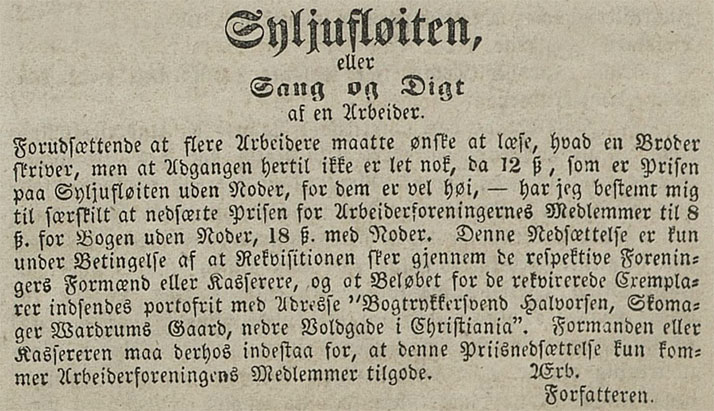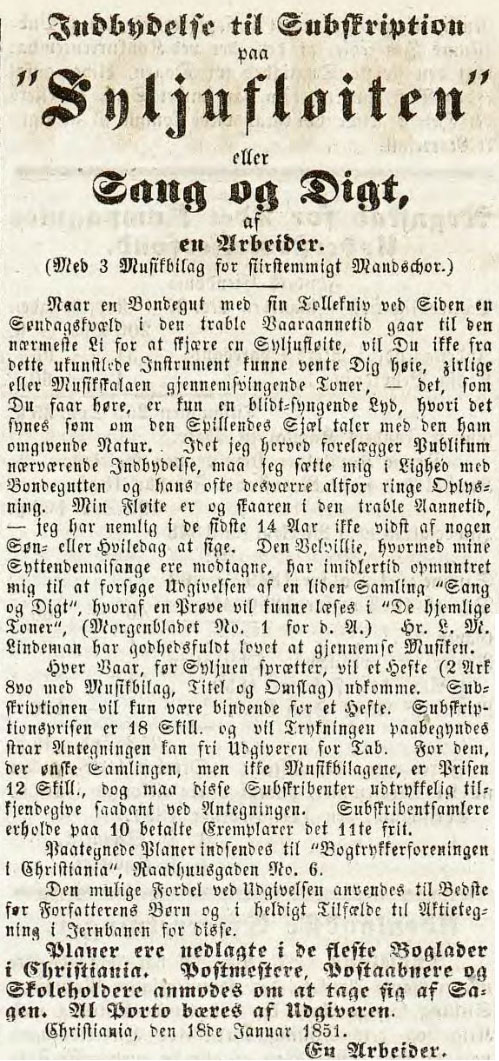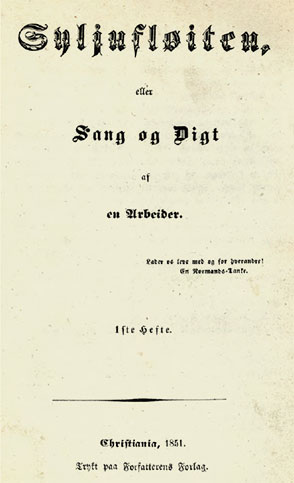
Typograf Christopher Daniel Grøndahls utgivelse fra 1851
Syljufløiten: tidlig norsk arbeiderdikting
Diktsamlingen Syljufløiten (seljefløyten i moderne språkdrakt) ble gitt ut i 1851. Forfatteren er «en Arbeider», som vi vet var typografen Christopher Daniel Grøndahl. Han var en ledende kraft i en tidlig organisering blant boktrykkersvennene i Christiania – Bogtrykkerforeningen af 1849.
I tillegg til at Syljufløiten er et uttrykk for en poetisk, skrivefør arbeiders tanker, inneholder den også politiske synspunkter som kaster lys over tidens meningsforskjeller i arbeiderklassen. Dette var nemlig den perioden da Marcus Thranes radikale arbeiderforeninger spilte en stor rolle i Norges politiske liv.
«Indbydelse til Subscription paa ‘Syljufløiten’ eller Sang og Digt, af en Arbeider» lyder overskriften i en annonse i Morgenbladet 7. mars 1851. Annonsen er datert 18. januar, så hvorfor det tok så lang tid å få den inn i bladet kan vi bare spekulere over.
I annonsen skriver forfatteren at det planlegges et hefte «Hver Vaar, før Syljuen sprætter» og trykkingen vil begynne når antall abonnenter er stort nok til at utgiveren ikke går med tap. Prisen for ett hefte var 18 skilling med noter og 12 skilling uten. Størrelsen på heftet skal være to ark i størrelse oktav (ca. A5 i moderne mål).
Liste for å tegne abonnenter var lagt ut i de fleste boglader i Christiania. «Postmestere, Postaabnere og Skoleholdere anmodes om at tage sig af Sagen.» Listene med abonnenter skal sendes inn til «Bogtrykkerforeningen i Christiania», Rådhusgaten 6.
Syljefløiten-annonser i Morgenbladet og i Arbeiderforeningernes Blad
Den 10. mai samme år står det også en annonse i Arbeiderforeningernes Blad, der heftet annonseres til foreningens medlemmer for 8 skilling uten noter og 18 skilling med noter.
Det er to ulike diktere som har bidratt til Syljufløiten. Først og fremst Christopher David Grøndahl, som ga ut boken, men det er en forfatter til som beskrives slik i forordet: «Jeg har anmodet en Arbeider om at give Bidrag til min Fløite; hans Sange ere mærkede paa Foden...» Denne andre dikteren er kun navngitt som Martin K–.
Det utloves i annonsene at det skal komme flere hefter, men det kom ikke flere enn dette første.
Hvem var Christopher David Grøndahl?
Forfatteren av de fleste diktene er Christopher David Grøndahl, født 21. juni 1812 i Christiania og død 29. mars 1879 i Larvik.
«Denne Grøndahl var meget begavet og ville gjerne studere, men foreldrenes små kår hindret ham og han kom som læregutt i trykkeriet hos sin fars tremenning boktrykker Christopher Grøndahl. Han giftet seg i 1842 med en enke, Else «Birgitte» Olsdatter som døde i 1852...» I 1856 flyttet han til Larvik og ble faktor og utgiver av Laurvigs Blad, som begynte å komme ut to ganger i uken høsten 1857. (Gjengitt etter Boktrykker Christopher Grøndahls etterkommere.)
Christopher David Grøndahl hadde imidlertid en langt mer spennende personlig historie enn som så. I 1849 var han medlem i Bogtrykkerforeningen af 1849, der han var en av de ledende menn. Dette var en svenneforening med formål «at forbinde nyttig samvirken med selskabelig omgang». Han satt i styret da foreningen annonserte etter aviser og bøker i Morgenbladet i 1850. Bogtrykkerforeningen ba i notisen forleggere og utgivere om å få tilsendt eksemplarer av bøker til sitt bibliotek, og Chr. Grøndahl jr. var en av underskriverne. Senere var han en av de første underskriverne av brevet som ble sendt til arbeidsgiverne i 1855, da typografene ønsket å forbedre tariffen de hadde inngått noen år tidligere. Han må med andre ord ha vært en av de viktigste lederne for typografene i hovedstaden frem til han flyttet til Larvik i 1856.
«Bogtrykkerforeningen af 1849» var kanskje en del av Haandværkssvendenes centralforening som ikke hadde et helt godt forhold til arbeiderforeningene, som var ledet av Marcus Thrane. Dette skinner litt igjennom i innledningen i Syljufløiten, der Grøndahl kritiserer Arbeiderpetitionen, som «thranittene» hadde sendt til Kong Oscar I, for å gå for langt. Videre så ærer han Halling, som ikke kan være andre enn pastor Halling, som drev Enerhaugens arbeidersamfunn i konkurranse med Thranes arbeiderforening.
For videre lesning om Bogtrykkerforeningen af 1849 og typografenes tariff vises til boken Guttenberg 1872-1873 (utgitt av Oslo grafiske fagforening 2012).
Om det tekniske
Boken er trykket i nettoformat 12,0 cm bredde og 20,8 cm høyde. Det er trykket to ark – det vil si at trykkformatet for formen har vært om lag 48 cm x 42 cm, eller noe i nærheten av A2 i våre dagers standardformat. På hvert ark har det vært åtte sider på hver side av arket – med to ark i boken blir det til sammen 32 sider. Boken er trykket i A. Th. Nissens Bogtrykkeri ved N. F. Axelsen. Axelsen var faktor i Nissens trykkeri og det var ikke uvanlig at dette ble nevnt på denne måten. Bøkene ble nok satt og trykket av svennene (og læreguttene), mens faktoren stod for kvaliteten av det hele.
Typografien i Syljufløiten er i tidstypisk gotisk drakt: brødteksten er fraktur, men diktenes titler satt med hva skriftstøperiene den gang kalte «gothisk», som ligger nær salig Johan Gutenbergs skrifttyper i hans Bibel-trykk. I dag kaller man denne skriftgruppen tekstur. Gothisk brukes også i en linje på tittelbladet, der vi samtidig finner et par linjer med fet fraktur. Hovedlinjen «Syljufløiten» er satt med en forsiret fraktur.
Det skal i denne forbindelse kun kort nevnes at det allerede året før, i 1850, ble utgitt en sangbok av arbeiderforeningene (Arbeiderforeningernes Sangbog), der typografen Peter Wilhelm Bergh stod som utgiver. I denne boken er det ikke angitt forfattere og det er ikke greit å vite om det er Bergh eller andre som har skrevet diktene.